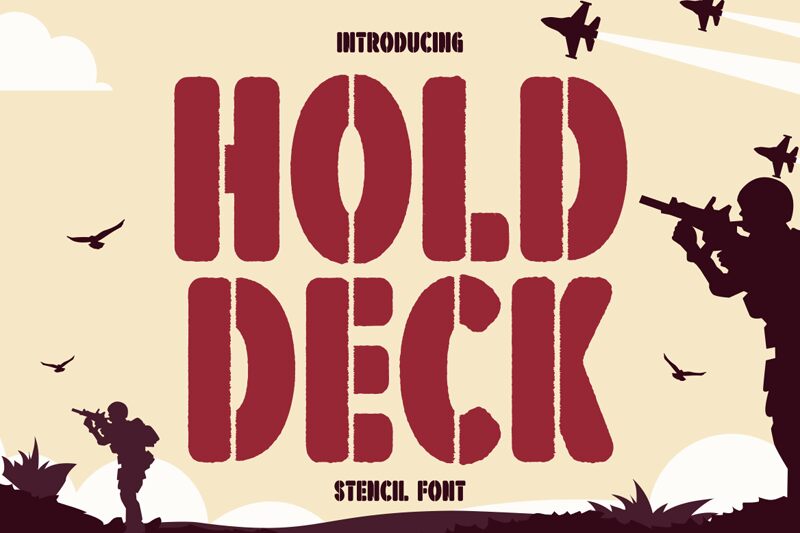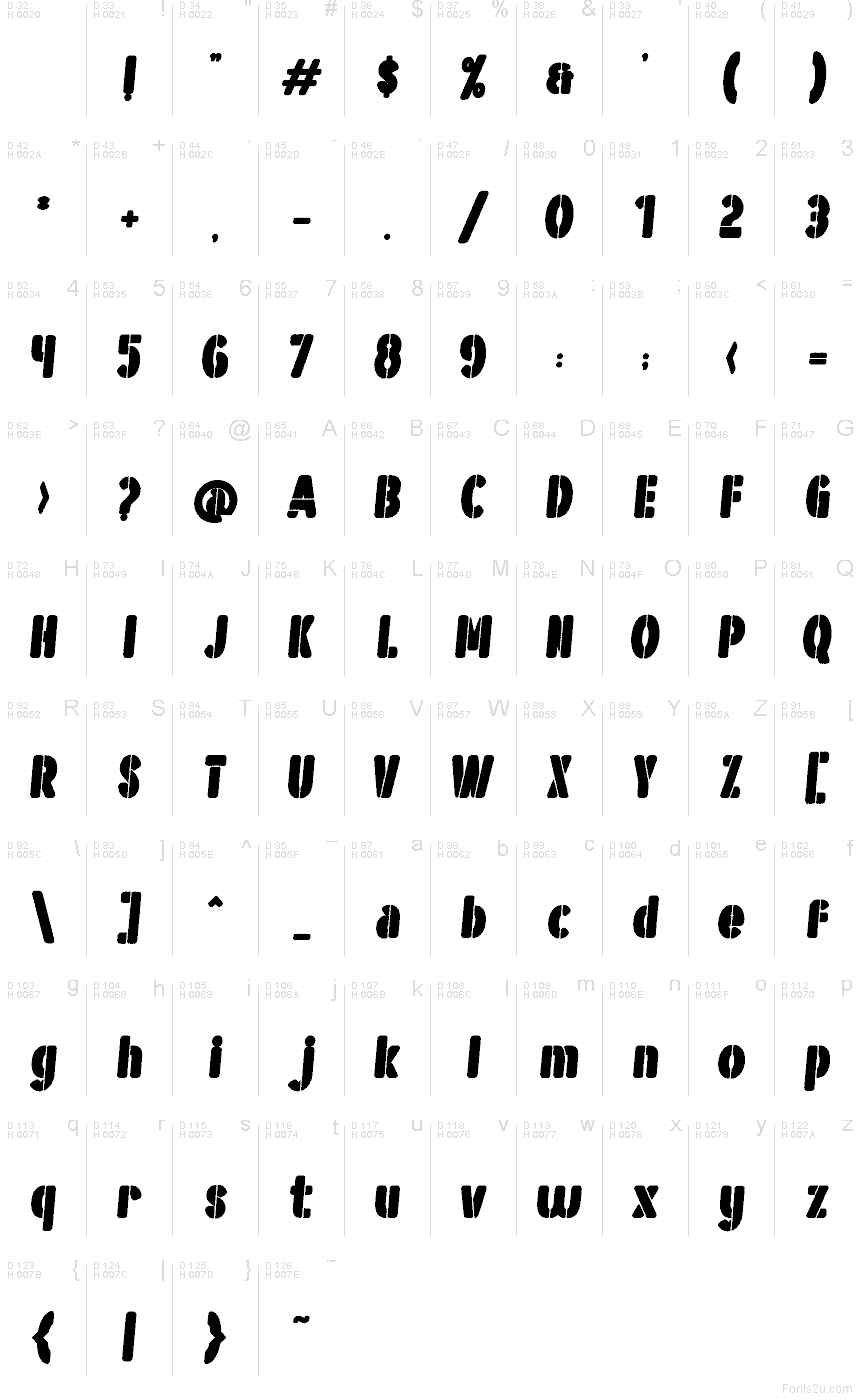
Hold Deck Italic
Shanaf Studioが提供するHold Deck Italicは、ミリタリー調のステンシルフォントです。フィールドでのマーキングのような荒々しい見た目と、狭い垂直の切り込みが特徴的です。文字は重厚かつコンパクトで、丸みを帯びた角とシンプルな幾何学的フォルムにより、ノスタルジックすぎない、タフで実用的な雰囲気を醸し出しています。
ポスターの見出しやアウトドア・タクティカル用品のパッケージ、ゲームのタイトルロゴ、イベントのグラフィック、そしてスタンプのようなミリタリーの質感を活かしたグッズ展開などに最適です。文字の形状が幅広く、要素がミニマルに削ぎ落とされているため、短い単語やカバーライン、バッジなどで、ステンシル特有の力強いリズムを最大限に活かせます。